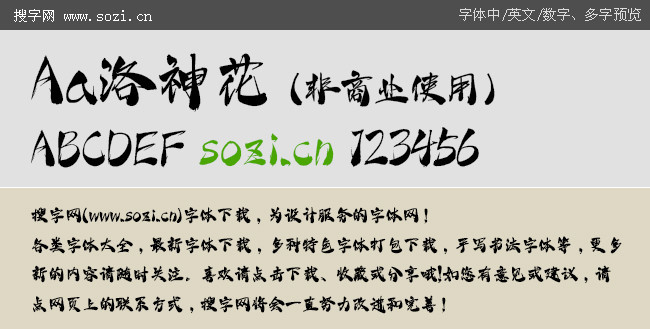
Aa洛神花
搜字網(wǎng)給大家提供一款A(yù)a洛神花(非商業(yè)使用)中文字體下載,該字體是一款手寫書法中文字體,字跡飛揚,筆斷意連,傳統(tǒng)與現(xiàn)代的手寫結(jié)合,適合書裝設(shè)計、包裝設(shè)計、海報設(shè)計等應(yīng)用(此字體為個人非商用版,商用可以聯(lián)系QQ:1006760504)。